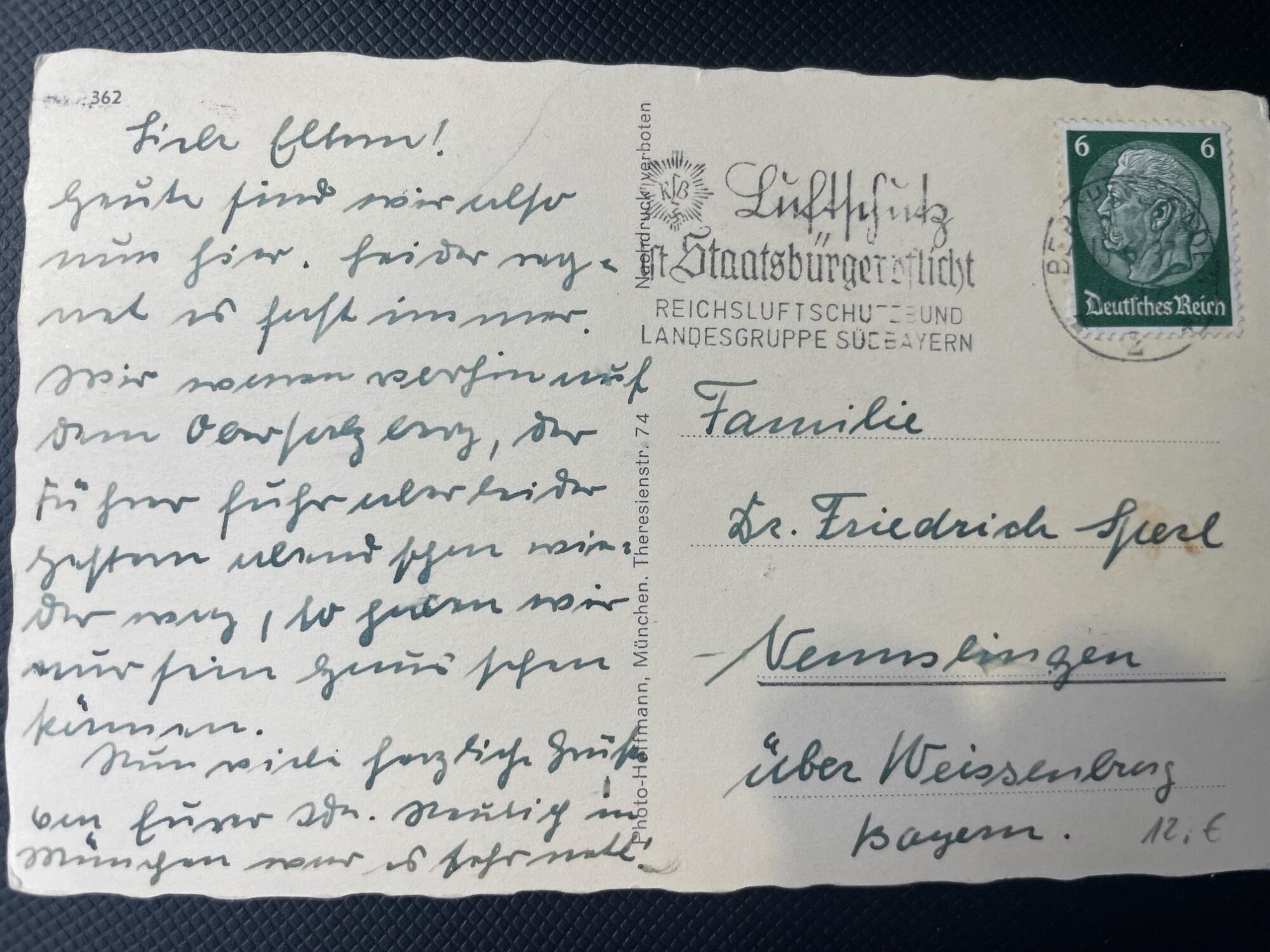
Handschrift entziffern
Hallo, habe diese Postkarte von einer Bekannten bekommen, kann sie aber nicht lesen. Kann das jemand entziffern?
Tourismus in Zeiten des Nationalsozialismus: ein Ausflug zum Obersalzberg mit der ausgedrückten Hoffnung, den Bewohner zu Gesicht zu bekommen, was "leider" nicht der Fall war, wie der Absender seinen Eltern mitteilt.
Darf ich nach dem Zusammenhang fragen, in dem die Karte aufgetaucht ist? Wenn es um eine Recherche der eigenen Familiengeschichte geht, bin ich bei der Transkription gern behilflich. Wenn es sich um Nazi-Memorabilia handelt ("12,- €"), eher nicht.
Vielen Dank! Ich wohne in den USA, wo meine Bekannte (Amerikanerin) als Geschichtslehrerin an einer high school arbeitet. Sie war im Sommer in Deutschland und hat diese Postkarte auf einem Flohmarkt gekauft. Sie wollte den Inhalt ihren Klassen teilen, da sie gerade über den 2. Weltkrieg lernen. Also, es geht nicht um die eigene Familiengeschichte, aber um Bildung. Ich unterrichte auch Deutsch hier an der gleichen high school und würde den Inhalt und die Schrift auch gern mit meinen Deutschklassen teilen.
Liebe Eltern!
Heute sind wir also nun hier. Leider regnet es fast immer. Wir waren vorhin auf dem Obersalzberg, der Führer fuhr aber leider gestern abend schon wieder weg, so haben wir nur sein Haus sehen können.
Nun viele herzliche Grüße von Eurer Ida. Neulig in München war es sehr nett!
Ich nehme an, auf der Vorderseite der Karte ist tatsächlich der Obersalzberg abgebildet, richtig?
Ich habe die Karte mal spaßeshalber durch die automatische (Kurrent-)Schrifterkennung von Transkribus gejagt:
Ergebnis, wie zu erwarten, leider unzureichend. Bei sehr sauber geschriebenen Dokumenten in Kurrentschrift bringt die Software ganz passable Ergebnisse (in jedem Fall besser, als die Schrift gar nicht lesen zu können). Die Postkarte ist leider zu hastig und "unsauber" geschrieben, so dass die Software streikt.
P.S.: Als ich vor einigen Jahren begonnen habe, für ein wissenschaftliches Projekt Kurrentschrift zu lernen, habe ich das übrigens mit einem amerikanischen Lehrbuch getan. Es war das erste, das ich in der Bibliothek gefunden habe, und es stellte sich als sehr gute Grundlage heraus. Mittlerweile können ja auch die meisten Deutschen Kurrentschrift nicht mehr lesen.
Ich nehme an, auf der Vorderseite der Karte ist tatsächlich der Obersalzberg abgebildet, richtig?
Jenes ist die Vorderseite, das Bild spar ich mir mal zu posten:
Erstmal vielen herzlichen Dank für die Hilfe mit dem Entziffern! Ich bin immer noch sehr erstaunt, wie sehr sich die Schreibschrift geändert hat, so dass ich, als Laie, kaum ein Wort lesen konnte. Habe auch zum ersten Mal von der Kurrentschrift gehört. Man lernt nie aus.
Meinen Deutschklassen habe ich die Postkarte heute schon mal gezeigt und sie haben versucht einzelne Buchstaben zu identifizieren. Das war ganz amüsant für uns alle.
Die Vorderseite der Postkarte war entsprechend interessant für die Schüler, im historischen Sinne (Abbildung vom "Führer"). Sehr viele amerikanische Schüler interessieren sich für die deutsche Geschichte, besonders das Deutsche Reich und 2. Weltkrieg, was den Inhalt des Geschriebenen umso faszinierender macht.
Für die Geschichtsklassen hier (bin in Maryland) ist es natürlich ein ganz tolles Beispiel von authentischen historischen Quellen. Vielen Dank also nochmal!